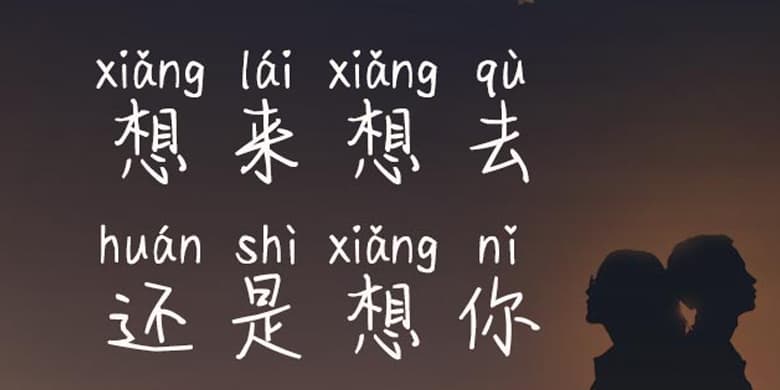
品牌:方正手迹设计师:刘晔发行时间:2020字库编码:大陆简体(GB2312-80)分类:常规书写·硬笔字体属性:精品字
行笔流畅圆熟,温润秀劲,结构严谨,一如日常书写,个性平易亲切。适用于现代诗歌、短文的排版以及文化、商业类品牌的广告语设计。
品牌:方正手迹设计师:刘晔发行时间:2020字库编码:大陆简体(GB2312-80)分类:常规书写·硬笔字体属性:精品字
行笔流畅圆熟,温润秀劲,结构严谨,一如日常书写,个性平易亲切。适用于现代诗歌、短文的排版以及文化、商业类品牌的广告语设计。